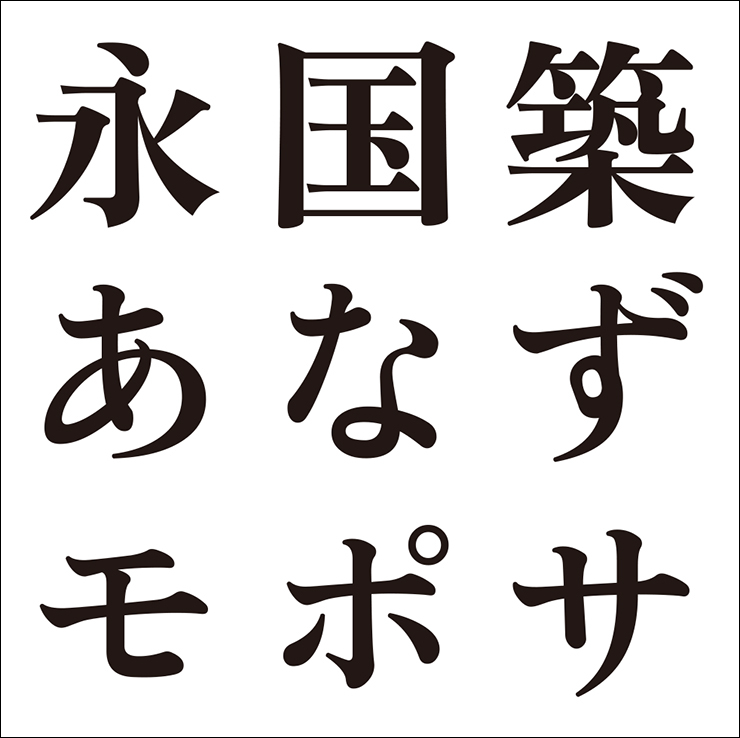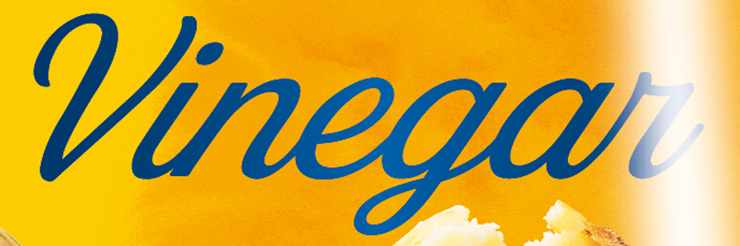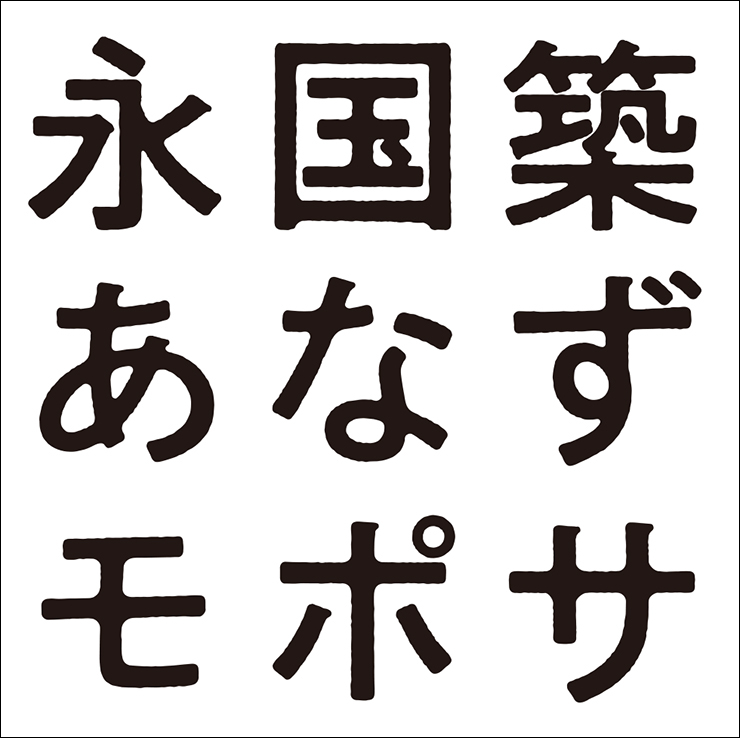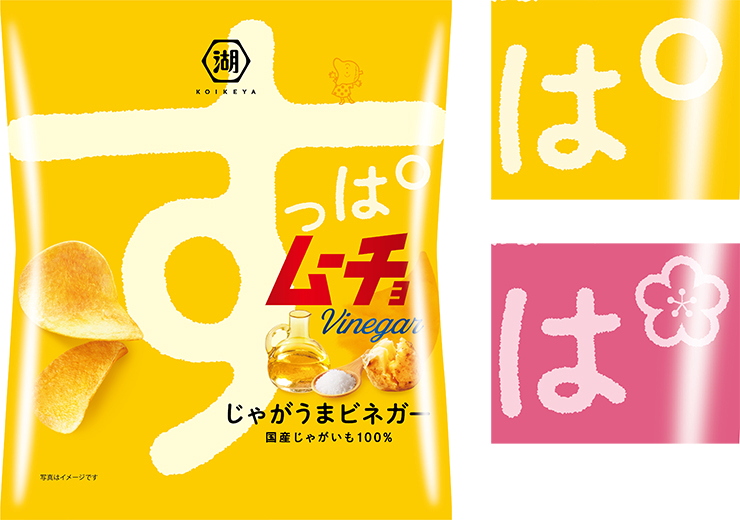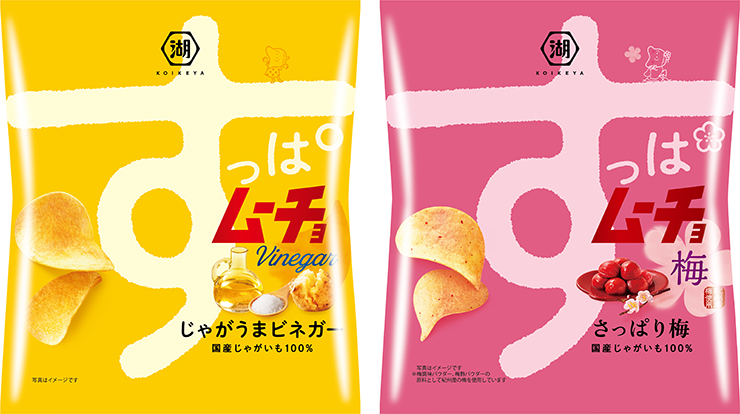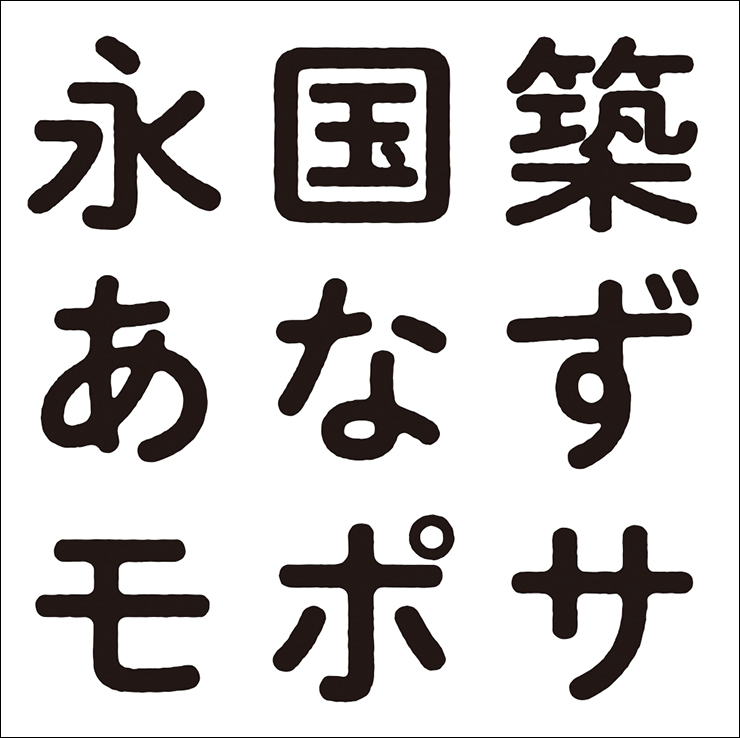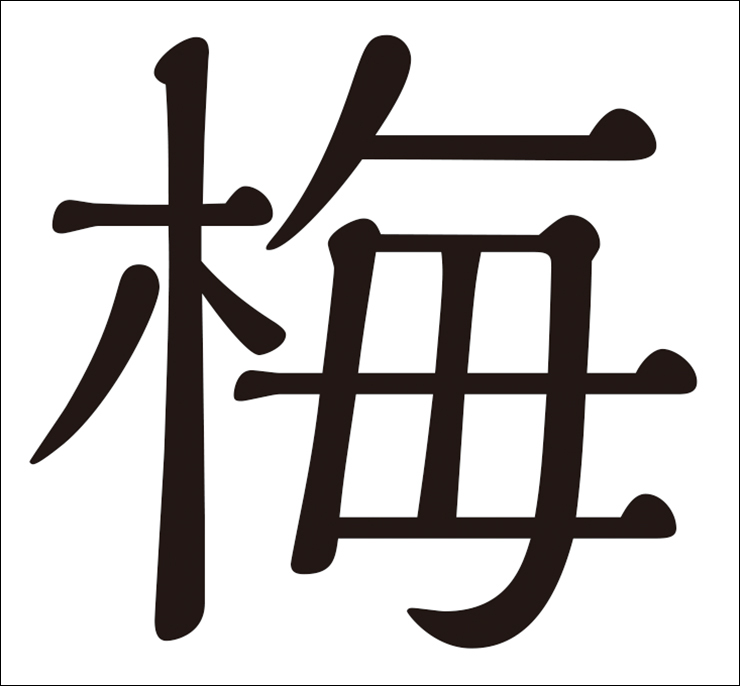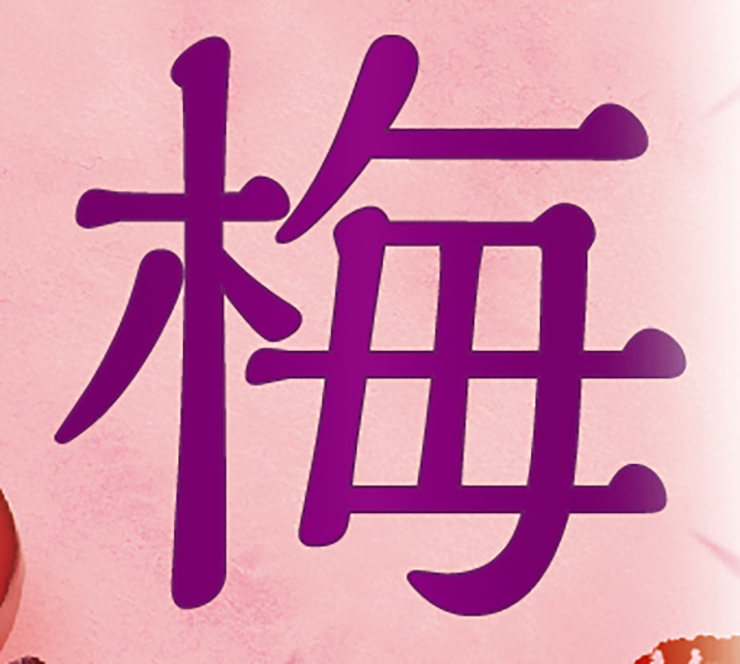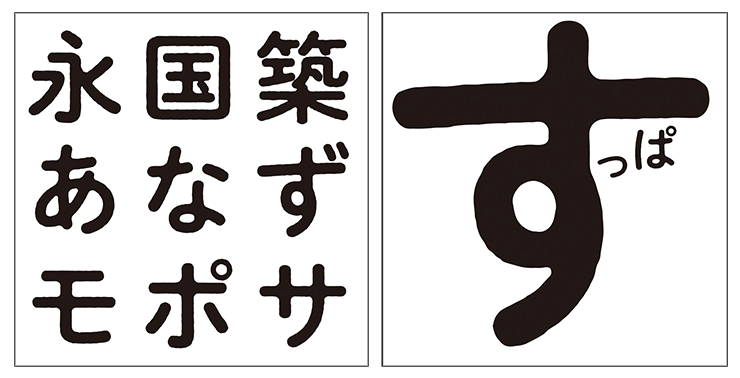
お菓子『すっぱムーチョ じゃがうまビネガー』『すっぱムーチョ さっぱり梅』の商品パッケージの使用フォントを紹介
『すっぱムーチョ じゃがうまビネガー』『すっぱムーチョ さっぱり梅』パッケージ/2022/湖池屋
●Creative Director:石井 原[ネアンデルタール]
●Art Director+Designer:松野下 亮[ネアンデルタール]、馬場としのり[ネアンデルタール]
今回は湖池屋のポテトチップス『すっぱムーチョ じゃがうまビネガー』『すっぱムーチョ さっぱり梅』のパッケージで使用されているフォントを紹介。
*本記事はデザイン構成において重要な「フォント」の選定プロセスや加工方法を、プロの実例から紐解いてデザイン制作に役立てる連載です。
じんわり滲んだニュアンス感のある文字で現代的な癒しを表現
すっぱいだけでなく、爽快な刺激と素材の旨味が感じられる味わいで人気のポテトチップス『すっぱムーチョ』のパッケージ。ビネガーのまろやかな酸味とじゃがいもの旨みが印象的な『じゃがうまビネガー』、梅のほんのりやわらかな酸味やじゅわっとした甘み、じゃがいもの旨みがクセになる『さっぱり梅』の2種類のフレーバーがラインアップされている。
“リフレッシュ&リラックス”をコンセプトにリニューアルされた新パッケージでは、『すっぱムーチョ』の味わいや商品特性が、現代的な癒しを感じさせる文字や配色、ビジュアルなどで表現されている。デザインを担当したクリエイティブカンパニー「ネアンデルタール」によると「リフレッシュしたい。癒されたい。そんな現代人の気持ちに寄り添う商品であることを念頭にデザインしました。じゃがいもの旨味と絶妙なバランスのビネガー・梅の酸味、ブランドの持つ歴史と愛嬌、誠実さを体現するパッケージにフルリニューアルしています」とのこと。
Font.01「秀英にじみ丸ゴシック」
インクの滲みを感じさせる文字でほっこりするような癒し感を演出
「商品ロゴ」部分
「秀英にじみ丸ゴシック」(モリサワ)
商品ロゴのうち「すっぱ」部分はインクのにじみを再現した温かみのある丸ゴシック体「秀英にじみ丸ゴシック」(モリサワ)がベースに。どこかほっこりするような“癒し”感があり、じんわりと滲んだアウトラインが背景に馴染んでみえるため選択された。
ネアンデルタールによれば「『す』にインパクトを持たせるため級数に差をつけて文字を組んでいるので、自然に見えるよう各文字の太さやアウトラインの馴染み感を細かく調整しています。また、フレーバーごとに『ぱ』の半濁音の形を変えて差別化をはかっています。商品名のうち『ムーチョ』部分は、同じムーチョブランドの商品『カラムーチョ』のロゴを使用しています」とのことだ。
Font.02「Stash Regular」
商品ロゴとの相性を考えスタンダードなスクリプト体に
フレーバー「Vinegar」部分
「Stash Regular」(J Foundry)
フレーバー「Vinegar」部分の文字は、“洋”のイメージを感じさせるスクリプト体「Stash Regular」(J Foundry)がベースに。ネアンデルタールによれば「商品ロゴとケンカしないよう、クセがなくスタンダードな筆記体を選びました。また文字を組んだ際にリズムがつくよう、斜体を強めています」とのこと。
Font.03「解ミン 宙 R」
商品の味覚を思わせるやわらかい印象の文字に
フレーバー「梅」部分
「解ミン 宙 R」(モリサワ)
フレーバー「梅」部分の文字は、“和”のイメージを感じさせる「解ミン 宙 R」(モリサワ)がベースに。明朝体に隷書の特徴を取り入れた独特のフォルムが、商品のイメージにマッチしていたため選択された。
ネアンデルタールによれば「『梅』という文字自体が商品の味覚に直結しているので、少しやわらかい印象を持つ書体を選びました。ウェイトはR(レギュラー)がベースですが、他の要素とのバランスを考えてレギュラーとミディアムの間くらいの太さになるよう加工しています」とのこと。
Font.04「秀英にじみ丸ゴシック」
素材の旨味を意識して温かみのある丸ゴシックを選択
フレーバー名称「じゃがうまビネガー」部分
「秀英にじみ丸ゴシック」(モリサワ)
フレーバーの名称「じゃがうまビネガー」部分の文字は、商品ロゴのベースと同じ「秀英にじみ丸ゴシック」(モリサワ)に。素材であるじゃがいもの旨味や、「じゃがうま」という言葉が持つ印象を考慮してインクの滲みを再現した温かみのある書体が選択された。
Font.05「ZENオールド明朝 H」
“和”を感じさせるスタンダードな明朝体に
フレーバー名称「さっぱり梅」部分
「ZENオールド明朝 H」(エイワン)
フレーバーの名称「さっぱり梅」部分の文字は、オーソドックスな骨格を持つオールドスタイルの明朝体「ZENオールド明朝 H」(エイワン)に。“和”を感じさせる書体で、かつ「解ミン 宙」と差別化できるため選択された。
Font.06「秀英にじみ角ゴシック金 B」
商品ロゴに馴染むよう同じルーツの書体を
「キャッチ」部分
「秀英にじみ角ゴシック金 B」(モリサワ)
キャッチ「国産じゃがいも100%」部分の文字はインクのにじみを再現した「秀英にじみ角ゴシック金 B」(モリサワ)がベースに。商品ロゴの「すっぱ」の文字と馴染むように、同じルーツを持つ書体が選択された。小さめの文字サイズで使用するため、若干文字を太めて可読性を高める工夫がされている。